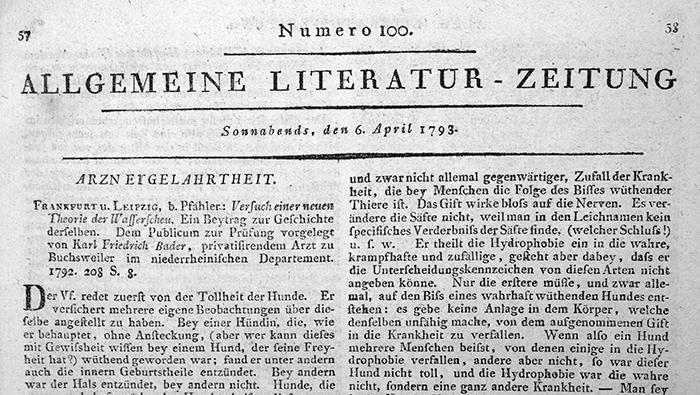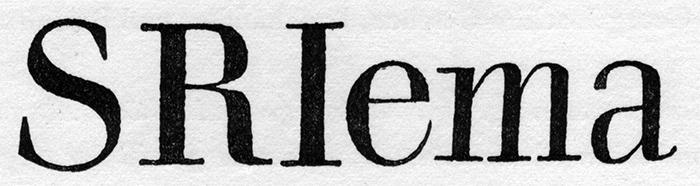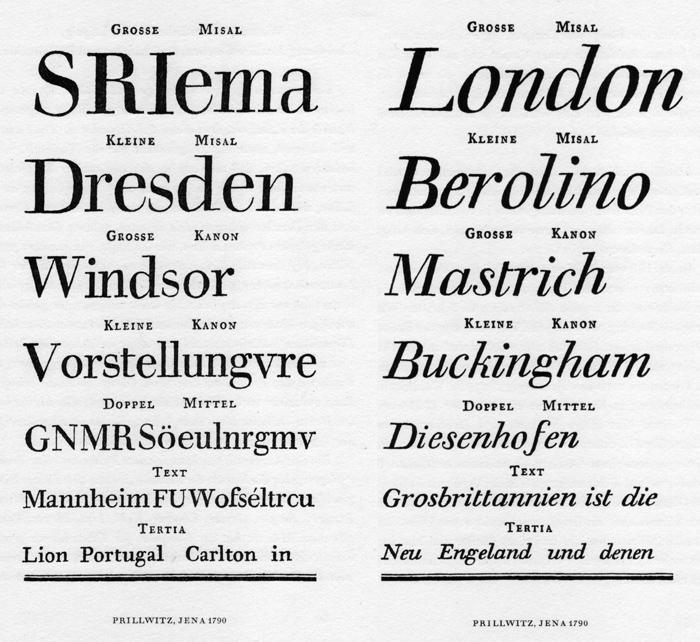
- circa 1790
- Antiqua statisch
- Versaleszett:
- enthalten
Die Klassizistischen Schriften entwickelten sich im Laufe des 18. Jahrhunderts vor allem in Frankreich (Fournier, Didot) und Italien (Bodoni). In Deutschland blieb indes die gebrochene Schrift vorherrschend. Doch die deutschen Gelehrten der Zeit fanden zunehmend Gefallen an der besonderen Anmutung des klassizistischen Schriftstiles. Johann Friedrich Unger hatte eine besondere Vorliebe für sie und vertrieb die Lettern von Didot in Deutschland. Wenig überraschend machten sich aber auch rasch deutsche Stempelschneider daran, die Didot’schen Lettern in mehr oder weniger abgewandelter Form herzustellen. Zu ihnen gehörte zum Beispiel der Jenaer Schriftgießer Johann Carl Ludwig Prillwitz. Prillwitz war in der Universitätsstadt Jena gut im Geschäft. Er bestückte gegen Ende des 18. Jahrhunderts die Allgemeine Literaturzeitung mit seinen Lettern, die mit Autoren wie Goethe, Schiller, Kant, Fichte und Humboldt zur auflagenstärksten Zeitung ihrer Art und Zeit wurde. Im Intelligenzblatt des Journals des Luxus und der Moden des Weimarer Verlegers Friedrich Justin Bertuch ließ Prillwitz 1790 annoncieren:
»Die Beförderung der Typographischen Schönheit war von jeher der Zweck meiner Bemühungen und Arbeiten; zu welcher mich immer die Betrachtung der schönen Schriften von Baskerville, Bodoni und Didot, deren Anblick dem Auge so wohl thut, aufmunterte; ich fürchtete aber immer daß die teutschen Druckereyen einem Schriftgießer den sehr beträchtlichen Aufwand, den er an ein vollständiges Sortiment Schriften in diesem Geschmacke wagen müsse, nicht vergüten möchten. Die Erfahrung aber hat meine Furcht widerlegt, da ich sehe, daß sowohl unser geehrtes Publicum als unsere Herren Buchhändler und Buchdrucker Geschmak daran finden, so habe ich es gewagt, und ein vollständiges Sortiment neuer Didotscher Lettern, als in keiner teutschen Schriftgießerey noch existiert, geschnitten, lege hierbey die Proben davon dem hochzuehrenden Publico dar, und offerire sämtl. Herren Buchhändlern und Buchdruckern meine neuen Didotschen Schriften um folgende gewiß sehr billige Preise […]«
Über die tatsächliche Qualität der Prillwitz-Typen stritt man sich damals wie heute. Unger, der hierzulande das exklusive Vertriebsrecht für die Didot-Lettern besaß, waren die Prillwitz-Typen, die auch noch ausdrücklich als Didot’sche Lettern angepriesen wurden, verständlicherweise ein Dorn im Auge. Er schickte eigens Prillwitz-Proben zu Didot, um sich von ihm eine mangelhafte Qualität bescheinigen zu lassen. Die Antwort, die erwartungsgemäß wenig Gutes über die Prillwitz-Lettern enthielt, ließ Unger als Warnung an Verleger, Buchdrucker und »Nachahmer« unter den Stempelschneidern in verschiedenen Blättern – darunter auch der Allgemeinen Literaturzeitung – abdrucken.
Andere Stimmen lobten dagegen die Arbeit von Prillwitz im Speziellen und auch die Bestrebungen im Allgemeinen, den Stil der Didot’schen Lettern von deutschen Stempelschneidern nachempfinden zu lassen. Neben Bertuch in Weimar ließ auch der bekannte Verleger Joachim Göschen in Leipzig in Prillwitz-Typen drucken. Über die von ihm verlegten Sämmtlichen Werke von Wieland ließ er in einer Annonce verlauten: »Die schönen lateinischen und dem Auge wolthuenden Lettern sind von Herrn Prillwitz in Jena geschnitten und gegossen.«
Anwendung in der Allgemeinen Literaturzeitung, 1793
Nach dem Einzug Napoleons ebbt die Begeisterung für die mit Frankreich assoziierten Lettern Anfang des 19. Jahrhunderts schlagartig ab und die Lettern von Prillwitz und Zeitgenossen wie Walbaum geraten in Vergessenheit. Im 20. Jahrhundert wird zunächst die Walbaum wiederentdeckt und erlangt durch Berthold große Verbreitung. Eine Neuinterpretation der Prillwitz nehmen Albert Kapr und Werner Schulze für den Fotosatz bei Typoart in Angriff. Sie wird in drei Schnitten (mager, kursiv, halbfett) ausgeführt. Als Digitalisierung sind die Fonts heute in zwei optischen Größen über Elsner + Flake erhältlich.
Eine umfassende Neuinterpretation, ausgehend von den Prillwitz-Originalmustern, nahm auch Ingo Preuß vor. Die Preußtype-Prillwitz wurde in drei echten optischen Größen (Book, Regular und Display) angelegt. Der als NP (NewsPrint) bezeichnete Schnitt ist speziell für einen Druck in kleinen Größen auf Zeitungspapier geschaffen und wurde aus der Display entwickelt. Für die Regular – und stärker noch die Book – wurde eine weiche und sehr lesefreundliche Outline durch eine s. g. Verschmitzung erreicht und in zahlreichen Testdrucken optimiert. Die Scharfkantigkeit und der übliche maximale Strichstärkenkontrast bekannter klassizistischer Schriften (Didot, Bodoni) wurde durch das Studium der originalen Drucke zugunsten einer sehr guten Lesbarkeit auch in kleinen Schriftgraden überarbeitet.
Die Schrift-Familie enthält alle wichtigen Zeichen für effizientes und typographisch hochwertiges Arbeiten: Kapitälchen mit entsprechenden Ziffern in Kapitälchenhöhe (tabellarisch und proportional), Minuskel- und Mediävalziffern (tabellarisch und proportional), Bruchziffern und einen kompletten Akzentsatz für alle lateinischen Schriften.